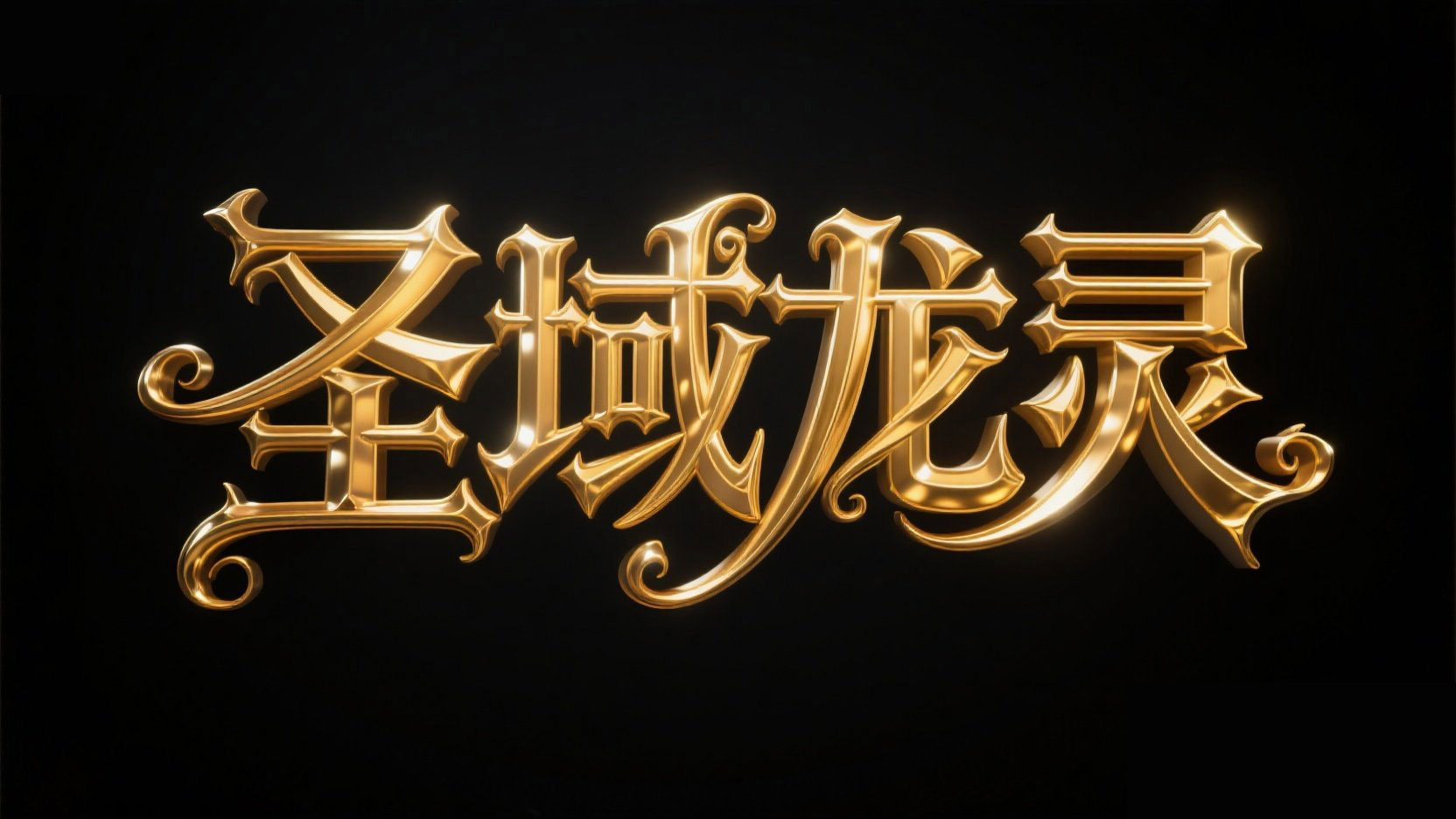
创作一个华丽魔幻风格字体文字内容为 “圣域龙灵”...
创作一个华丽魔幻风格字体文字内容为 “圣域龙灵”...AI字体提示词
游戏标题完整提示词可直接复制
风格定位
适合做风格探索与字形灵感延展。
适合场景
海报设计、品牌标题、电商设计、创意视觉
创作一个华丽魔幻风格字体文字内容为 “圣域龙灵”,字体为耀眼的金色,带有金属光泽和高光效果,呈现 3D 立体质感,笔画设计富有魔幻风格的装饰性细节,背景为干净的黑色。
可替换关键词
金属纸张肌理浮雕高对比立体阴影强笔触“圣域龙灵”字体为耀眼的金色呈现3D
生成建议
• 先保留核心风格词,再替换材质、颜色和光影词做多轮尝试。
• 如果用于品牌标题字,补充品牌气质、行业属性和情绪关键词。
• 如果用于海报或电商标题,额外强调大字、对比度和视觉冲击力。